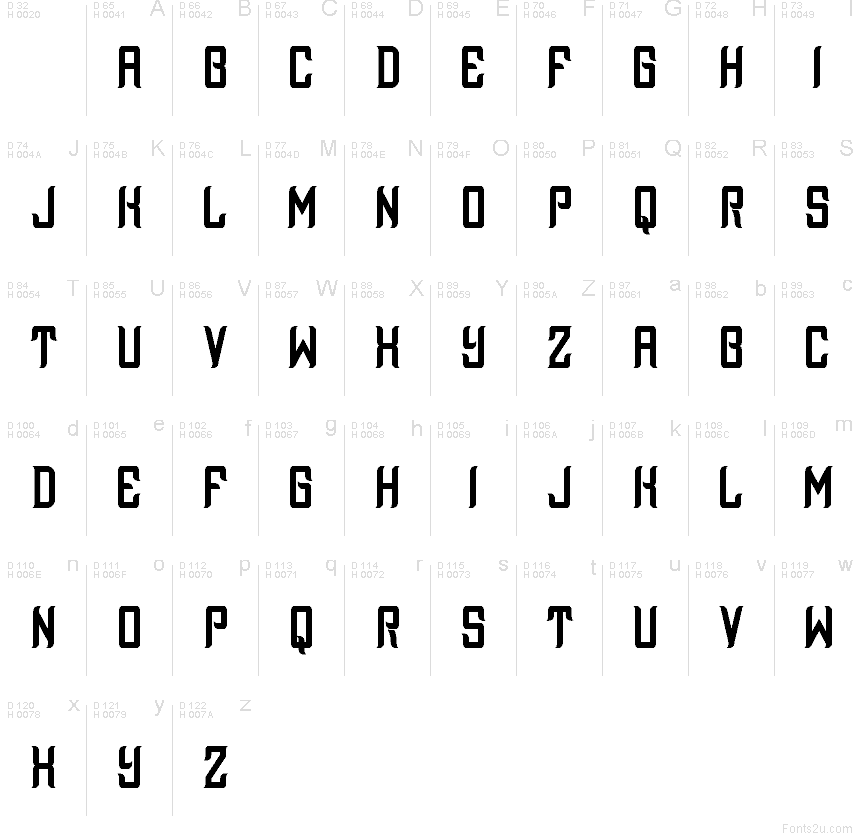
Assyrian Script od Vladimira Nikolica je bezplatné display písmo inspirované arabským stylem, s vysokými, těsně sázenými latinkovými znaky. Široké svislé tahy a úzké vnitřní výřezy vytvářejí výraznou pruhovanou texturu s hlubokými oblouky, které se opakují v celém písmovém obrazu.
Jeho opakující se sloupce mohou na plakátech ke kulturním akcím a ve výstavní grafice připomínat architektonické arkády a ornamentální bordury. Módní branding získává díky strohé výšce a tesaným tvarům dramatický ráz. Na obálkách publikací a propagačních materiálech pro divadelní či scénická představení se oblouky mohou stát součástí okolního vzoru, nikoli pouhým neutrálním textem.